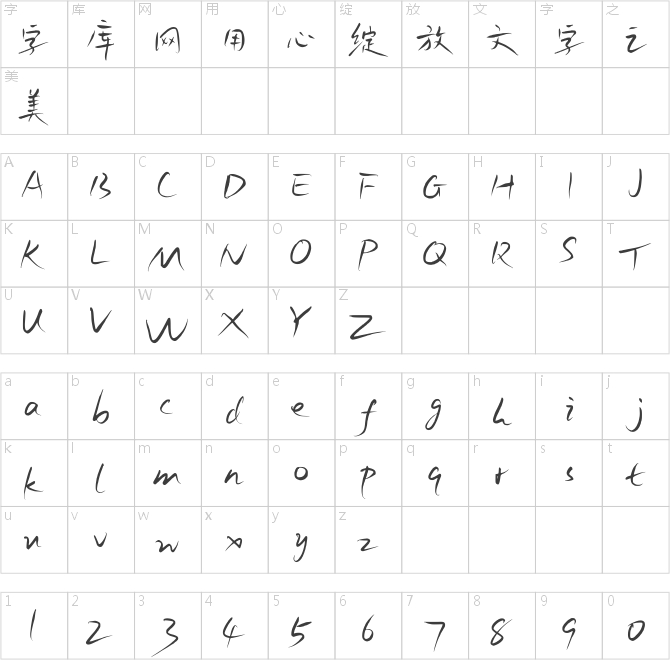
字體名稱: 鴻雷拙書簡體
這套字體寫于2021年6月份 命名為《鴻雷拙書簡體》 拙的本意就是拙略,“丑”的意思,因為寫完后才發現是真的丑,放在文件夾里一年半了,前幾天整理文件的時候沒有任何猶豫直接被我刪了。
鴻雷拙書簡體字體字庫是一款讓人賞心悅目、百看不厭的中文字體,適合各類廣告和產品包裝設計應用,字體大小6.2MB,格式為otf字體,上傳用戶是82年的拉菲,作者/版權方為鴻雷